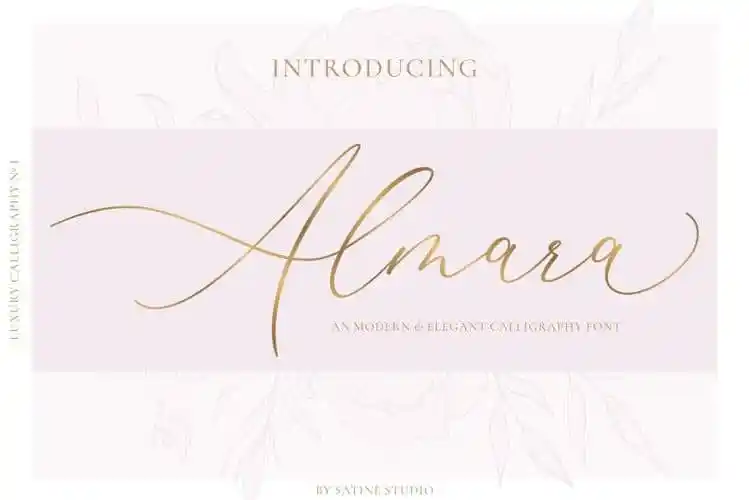
A Almara Calligraphy Font é uma deliciosa fonte escrita à mão com traços encantadores, desenvolvida pela Satin Studio para os mais atentos criativos. Essa nova fonte de calligrafia elegante e luxuosa pode ser usada em uma variedade de projetos: desde a criação de cartões de convite e postais para casamentos até o design de marca, embalagens e etiquetas de vinhos. Seja você designer gráfico ou simplesmente alguém que busca uma fonte perfeita para adicionar um toque único aos seus trabalhos, Almara tem tudo o que precisa: estilo elegante, suavidade na escrita à mão e uma aparência sofisticada. Ideal tanto para estilos convencionais quanto criativos, a fonte da Almara é certamente uma excelente escolha para quem valoriza personalização em cada projeto.